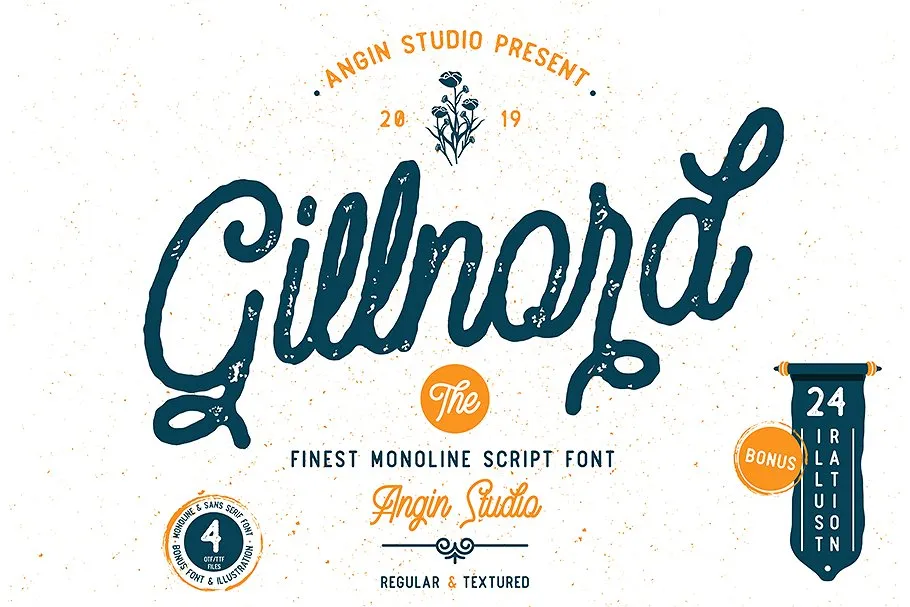
Gillnord Script Font – Download Grátis
Este é um novo adição à categoria dos tipos de fontes script, chamada Gillnord Script Font. Inspirado nos mercados rústicos vintage e sinalização do farol moderno de meados do século XX, esta fonte oferece uma experiência única e encantadora. Desenvolvida cuidadosamente com precisão, essa fonte tem curvas perfeitas, o que a torna diferenciada e atraente. Ela não apenas adicionará um toque vintage aos teus projetos, mas também dará mais elegância à tua criação. Ideal tanto para logos, marcas de marca, embalagens, outdoors ou qualquer outro projeto com um toque antigo. Esta é uma fonte perfeita para quem busca algo autêntico e sofisticado para seus designes.